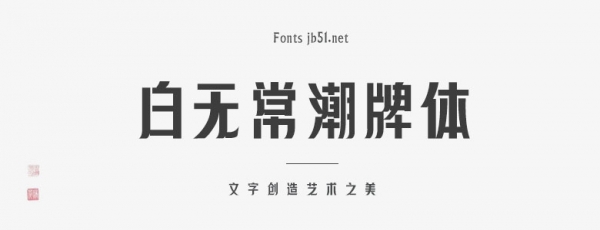
白無常潮牌體是一款極具個(gè)性的藝術(shù)字體,適合做標(biāo)題,稍微會(huì)個(gè)性一些,所以就叫潮牌體啦。具有很好的視覺感,適合于文化類的宣傳設(shè)計(jì)、商業(yè)類品牌的廣告和產(chǎn)品包裝設(shè)計(jì)以及個(gè)性化文字排版等較多場(chǎng)景。